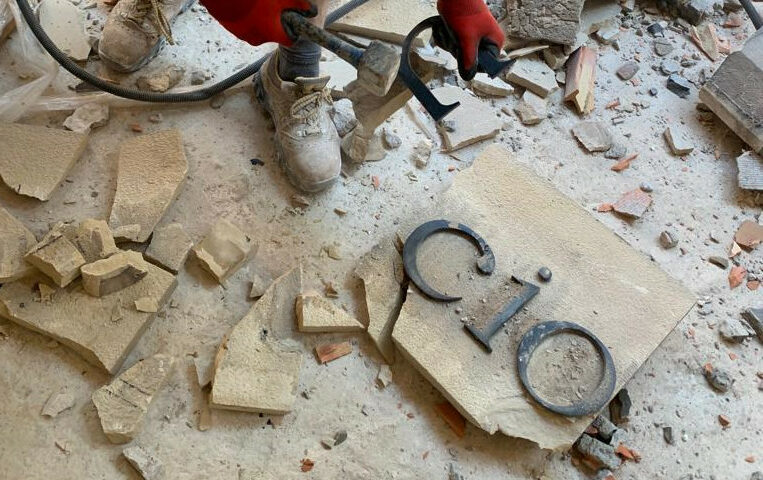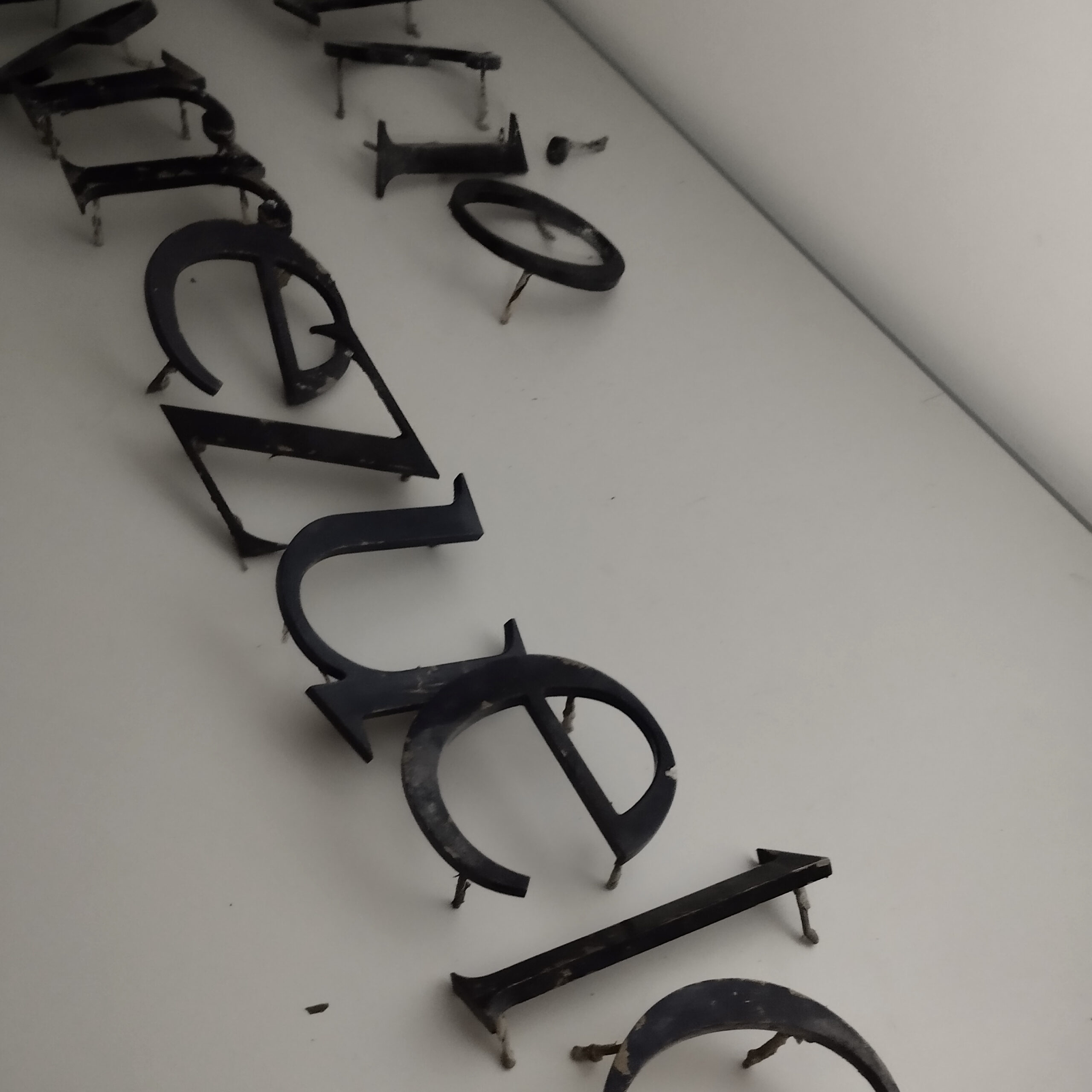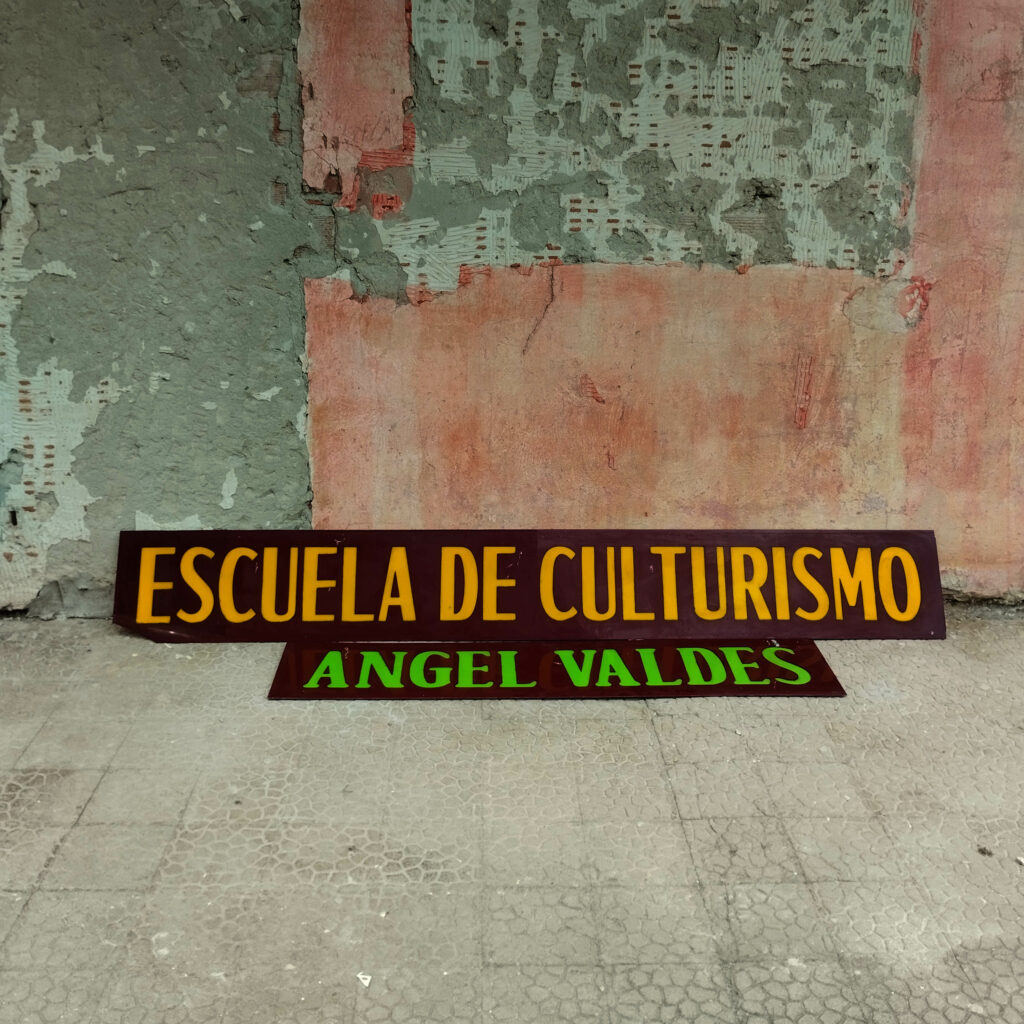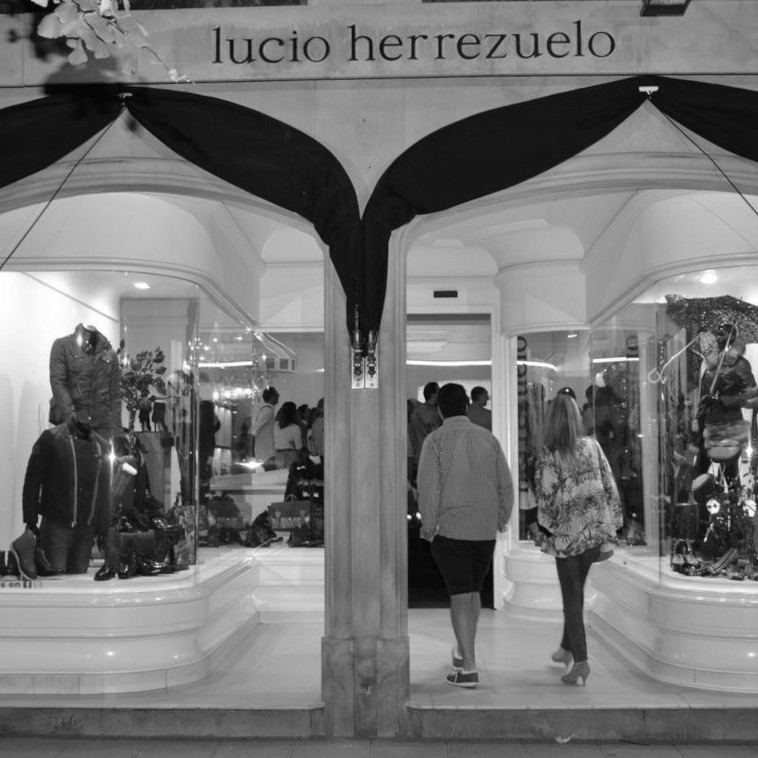
Escuela de Culturismo y Lucio Herrezuelo
Hoy os traemos dos rescates en que nuestros custodios han jugado un papel importante para poder salvarlos y que pudiésemos después ir a recoger y sumar en el archivo que estamos haciendo de Patrimonio Gráfico de Cantabria.
1. El cartel de la «Escuela de Culturismo de Angel Valdés» en General Dávila. Nos llegó un mensaje de que había obras en el local. Gracias a la gestiones de nuestra custodia y a la sensibilidad de su actual propietaria, Maria Dolores Hoz de la Escuela de Karate Gyakukan por conservarlo hasta que lo recogimos, se ha podido salvar este pedazo de historia del barrio que se remonta a los años 70.
2. Letras corporeas de la tienda de «Lucio Herrezuelo», en la calle Calvo Sotelo de Santander. Estábamos pendientes, y como siempre de un día para otro salta la alarma. Gracias a César Pombo, amigo del proyecto y custodio a la par de ser Memoria Viva del Comercio Local, pudo evitar que acabaran en el contenedor. Lucio Herrezuelo cerró sus puertas en 2018 tras más de 60 años de actividad. Siendo Beda Herrezuelo una de los referentes del diseño en la moda en España.